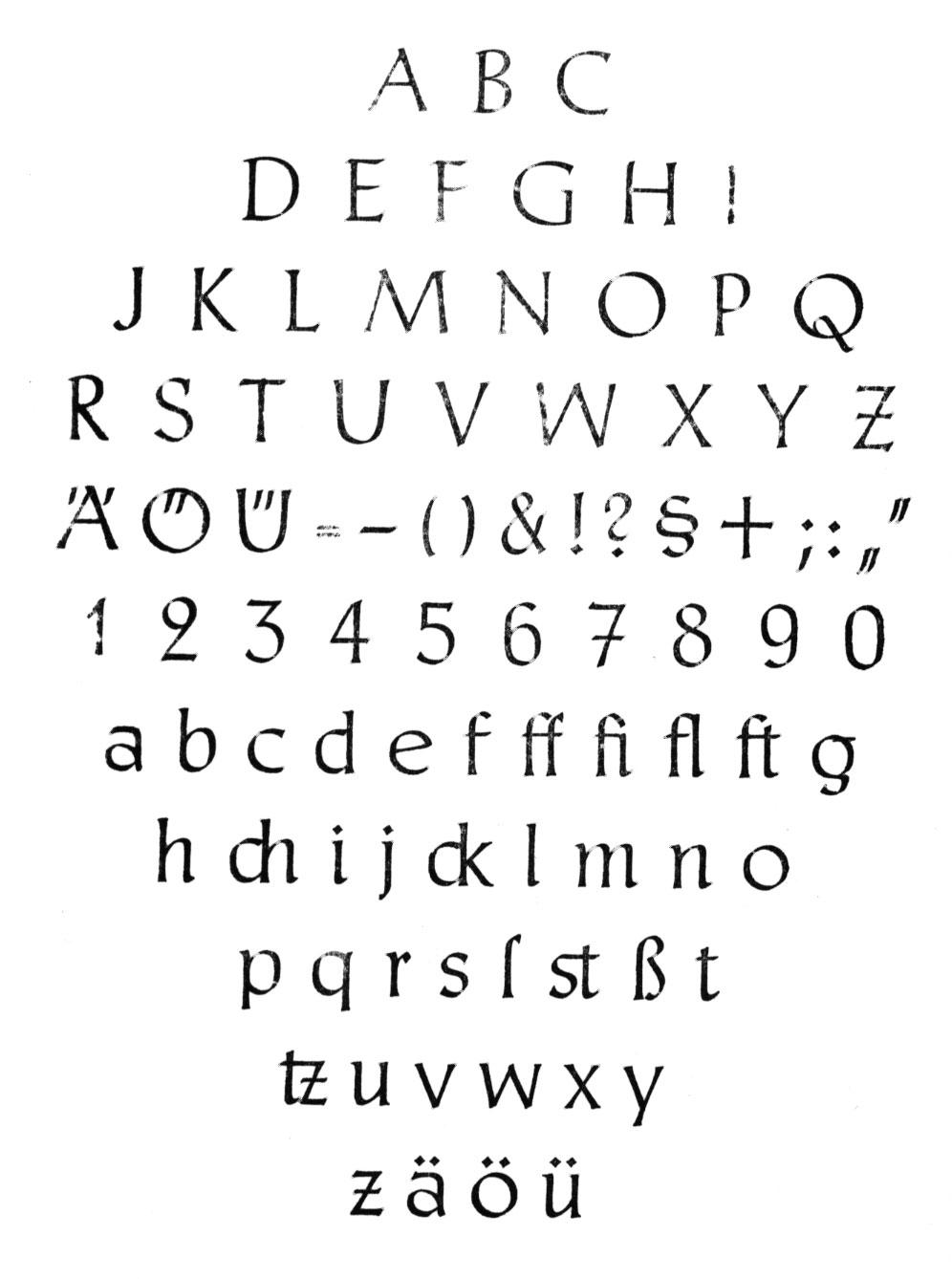
Welche Bleisatzschrift ist das?
Ist mir furchtbar peinlich, aber ich kann diese Bleisatzschrift nicht identifizieren ... Ist eine Komplettgußschrift, gefunden in den Tiefen eines Steckschriftkastens, der aus einer Setzerei aus Mecklenburg stammt. Sollte höchstwahrscheinlich aus einer deutschen Gießerei kommen, ich würde auf 1910 bis 1920 tippen, bin aber nicht sicher, weil ich aus dieser Zeit nicht so viele Schriftmuster habe. Hat ein bisserl was von der Post, auch von der Koch, ein bisschen Ehmke und ein bisschen was eigenes und hab ich noch nie (bewußt) gesehen.
Ist nur ein schneller Abzug, aber ich denke, die meisten Buchstaben sind halbwegs ausreichend zu erkennen. Leider fehlt das kleine k komplett ... schade. Ich finde vor allem das Q, das g und ÄÖÜ ausgesprochen hübsch. Danke schon mal vorab an alle Experten!
DANKE! Jetzt sehe ichs auch, dass sie doch besser in die vierziger passt ... Hab mich durch das Kalligrafische fälschlicherweise in das frühe 20. Jahrhundert schicken lassen ...